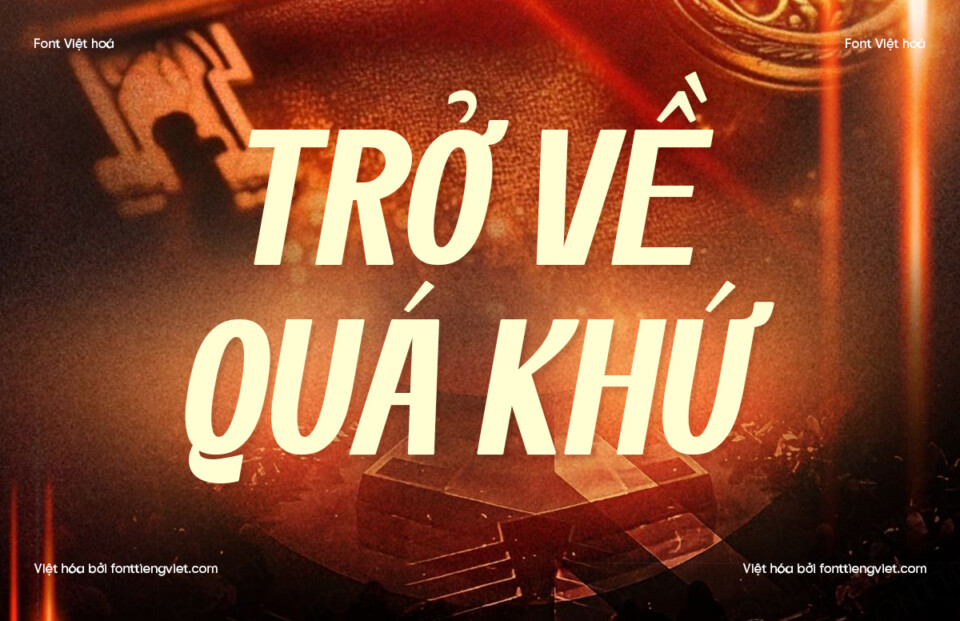
Font Việt hóa 1FTV VIP Blona Italic
Giới thiệu về Font Việt hóa 1FTV VIP Blona Italic
Trong thế giới đồ họa hiện đại, việc lựa chọn một bộ Font Miễn Phí chất lượng luôn là ưu tiên hàng đầu của các nhà thiết kế. Font Việt hóa 1FTV VIP Blona Italic nổi lên như một hiện tượng nhờ sự kết hợp hoàn hảo giữa nét chữ thanh mảnh và độ nghiêng tinh tế. Đây là phiên bản được tối ưu hóa riêng cho người dùng tại Việt Nam, khắc phục hoàn toàn các lỗi hiển thị dấu tiếng Việt vốn thường gặp ở những bộ font ngoại nhập. Với phong cách Italic đặc trưng, bộ font này mang lại cảm giác chuyển động, mềm mại nhưng vẫn giữ được sự chuyên nghiệp cần thiết cho mọi sản phẩm truyền thông từ học đường đến doanh nghiệp.
Đặc điểm nổi bật của Font Việt hóa 1FTV VIP Blona Italic
Thiết kế hiện đại và thanh lịch
Điểm nhấn lớn nhất của Font Việt hóa 1FTV VIP Blona Italic chính là những đường nét được bo tròn nhẹ nhàng kết hợp với độ nghiêng chuẩn xác. Điều này giúp văn bản trở nên dễ đọc hơn, đồng thời tạo ra một nhịp điệu thị giác lôi cuốn. Các ký tự được thiết kế với khoảng cách hợp lý, giúp tối ưu hóa không gian hiển thị trên cả màn hình kỹ thuật số lẫn bản in truyền thống. Sự thanh lịch của nó rất phù hợp để làm tiêu đề cho các bìa báo, tạp chí thời trang hoặc các bài thuyết trình tại trường học cần sự chỉn chu và tính thẩm mỹ cao.
Khả năng ứng dụng đa dạng trong thực tế
Dù bạn là một học sinh đang làm slide bài giảng hay một designer chuyên nghiệp thiết kế bộ nhận diện thương hiệu, Font Việt hóa 1FTV VIP Blona Italic đều có thể đáp ứng tốt. Font chữ này cực kỳ hiệu quả khi sử dụng cho các câu trích dẫn (quotes), thiệp mời đám cưới, hoặc các biểu ngữ quảng cáo đòi hỏi sự sang trọng. Khả năng tương thích tốt với các phần mềm thiết kế phổ biến như Adobe Photoshop, Illustrator và Canva giúp người dùng dễ dàng thao tác và sáng tạo mà không gặp bất kỳ rào cản kỹ thuật nào.
Cách tối ưu hóa Font Việt hóa 1FTV VIP Blona Italic trong thiết kế
Kết hợp màu sắc và bố cục
Để Font Việt hóa 1FTV VIP Blona Italic thực sự tỏa sáng, bạn nên kết hợp nó với các gam màu trung tính hoặc pastel. Độ nghiêng của font chữ này tạo cảm giác bay bổng, vì vậy khi đặt trên một nền hình ảnh tối giản, nội dung sẽ trở nên nổi bật và thu hút ánh nhìn ngay lập tức. Ngoài ra, việc kết hợp Blona Italic với một font chữ không chân (Sans-serif) ở phần nội dung chính sẽ tạo ra một sự tương phản tuyệt vời, giúp phân cấp thông tin một cách rõ ràng và khoa học nhất cho người xem.
Lưu ý khi sử dụng font chữ nghiêng
Khi sử dụng Font Việt hóa 1FTV VIP Blona Italic, người dùng nên tránh viết hoa toàn bộ các đoạn văn bản dài vì sẽ gây mỏi mắt. Thay vào đó, hãy dùng nó để nhấn mạnh các từ khóa quan trọng hoặc làm tiêu đề phụ. Việc điều chỉnh khoảng cách dòng (leading) rộng hơn một chút so với bình thường cũng sẽ giúp bộ font này phát huy tối đa vẻ đẹp thanh thoát vốn có của nó, tạo nên một tổng thể hài hòa và chuyên nghiệp cho tác phẩm của bạn.
Kết luận về bộ Font Việt hóa 1FTV VIP Blona Italic